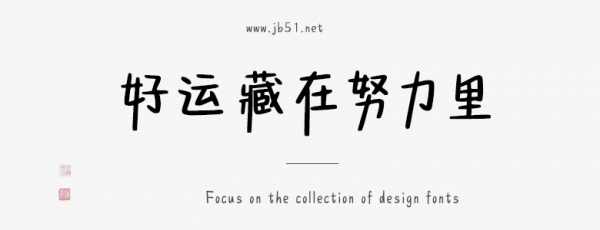
Aa好運(yùn)藏在努力里由Aa字庫(kù)出品的藝術(shù)字體,字體筆觸適中,書(shū)寫(xiě)流暢,適合應(yīng)用于藝術(shù)設(shè)計(jì)、平面宣傳設(shè)計(jì)、網(wǎng)頁(yè)設(shè)計(jì),書(shū)法字帖等領(lǐng)域。有需要的朋友快來(lái)本站下載使用吧。